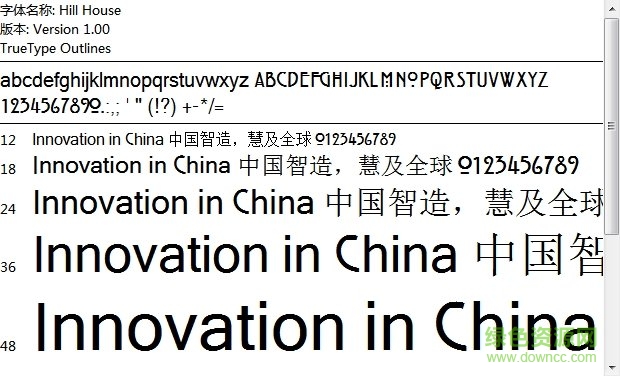
hill house字體,也稱作美國(guó)怪譚字體,是一款造型清爽、結(jié)構(gòu)突出的英文字體,中文端正英文圓潤(rùn),用作藝術(shù)設(shè)計(jì)再合適不過(guò),綠色資源網(wǎng)誠(chéng)意推薦!
hill house字體是一款適合活動(dòng)設(shè)計(jì)、英文裝飾的藝術(shù)字體,讓你的英文書(shū)寫(xiě)顯得更加大氣深沉,給人比較美好的視覺(jué)體驗(yàn)。